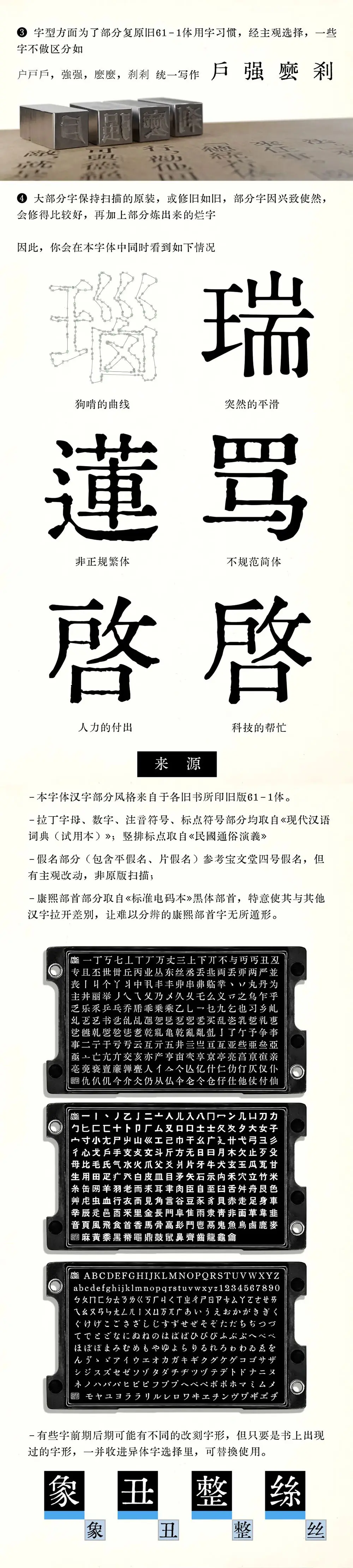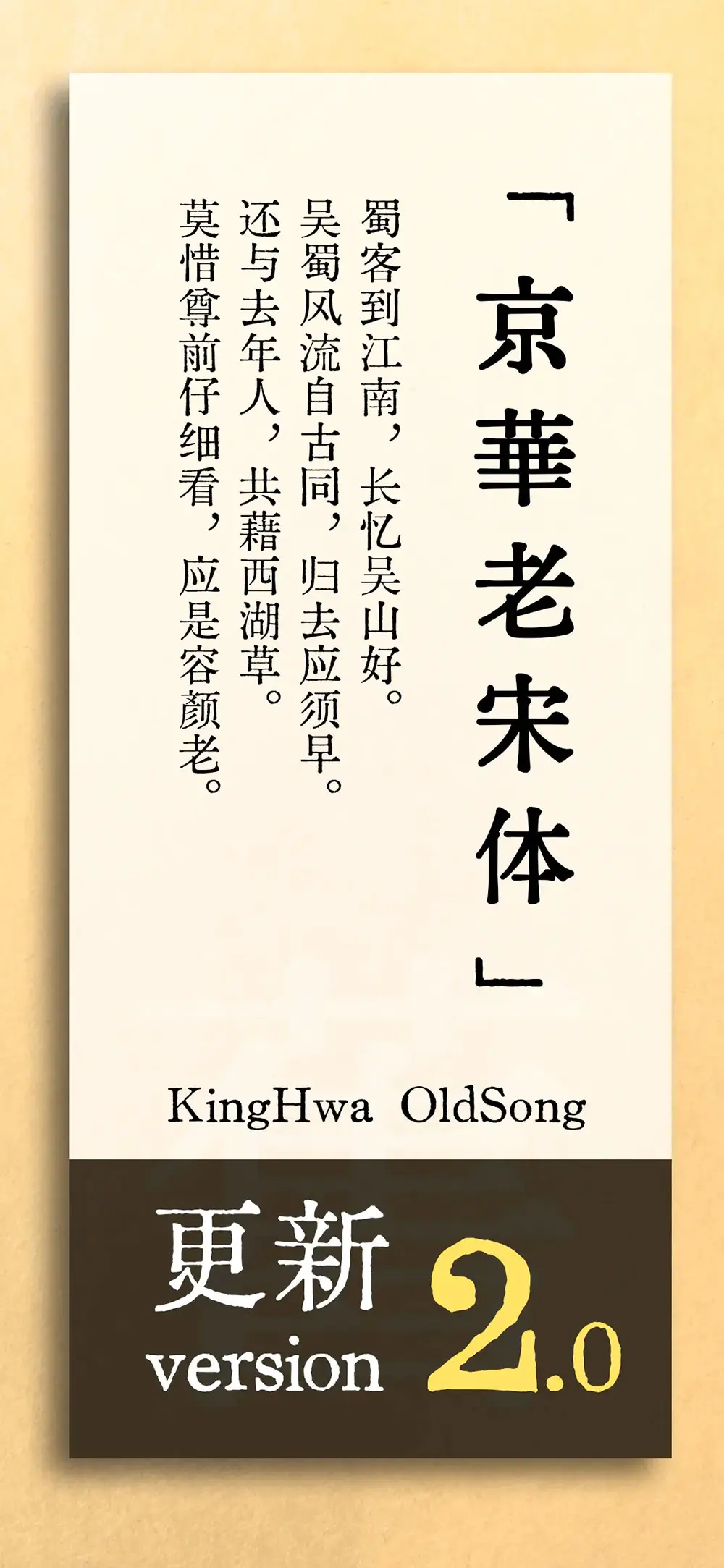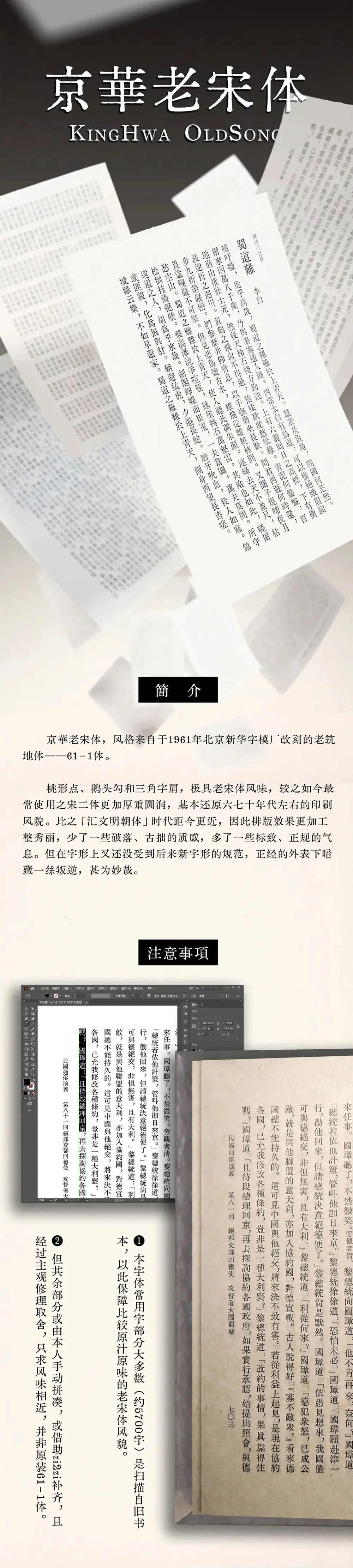
2022年年 6 月初,我(這裡的我指字體作者)發了一篇《尋找老宋體:試著探索一下 61-1 體》。要說為甚麼會去搞這番探索,正是因為那時我在做這款掃描字體。當時我為了收集字樣,遍查孔網舊書,尋覓老 61-1 體的印刷品。對 61-1 這個字體,越看越熟悉,慢慢發現了一些規律和特點,就稍微記錄整理了一下,作為一個階段性總結,彙集成了那篇東西。在那之後,我也繼續在收集字樣。時隔一年多,終於,我覺得這個字體弄得差不多可以用了,是時候該丟出來了。
慣例之發佈之前先講講故事,要說掃描鉛字的字體,之前我已經發過兩個了,這次怎麼又做了一個呢?嘛,首先,這幾個字體側重點還是不一樣
【匯文明朝體】當時做的想法是弄一個復原早期鉛字印刷品風格的字體。那個時候我對這些字體具體的來由、故事毫不瞭解,所以就只顧胡亂收集字樣。管他甚麼字號,甚麼來歷,只要是當時存在的老宋體,都往裡面填。整個就是一個不成體系的大雜燴。並且那時的很多鉛字字模破爛,加上紙張粗糙,印刷時油墨不均,再由我一掃描,一轉曲線,那真是,要多狗啃有多狗啃。但你還甭說,效果是真達到了,弄出來的字還真挺有當時印刷品內味兒。
而【築地五號】只是在做匯文明朝的過程中想要偷懶,妄圖把一個完整的明朝體見本整個收錄進去,結果發現風格不合適只好單獨分離出來,另成一個字體而來的。這個倒是成體系了,但是收字不多,沒法正常用。
於是我一直想弄套真正成體系,並且儘量不那麼狗啃的鉛字掃描字體出來。